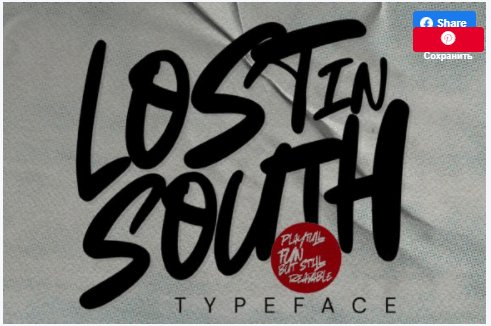
Lost in South Font
Lost in South - это стильный уличный шрифт с матовой краской. Этот шрифт подходит для таких дизайнов, как футболки, спортивная одежда, логотипы, реклама, одежда и т.д.